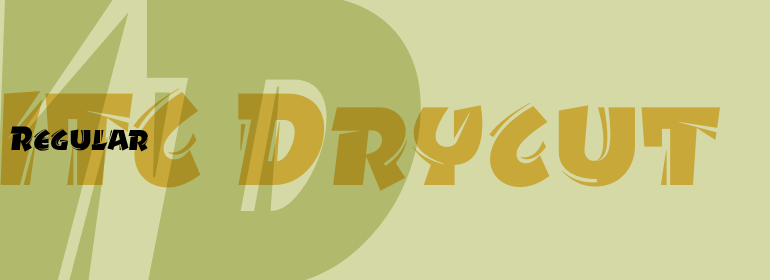
ITC Drycut™
ITC Drycut™,这款字体结构工整、笔画清晰,兼顾美观与易读性,适用于标题、正文、海报、包装、LOGO 等多种场景。字形优雅稳定,风格百搭耐看,适配日常排版与创意设计,让文字呈现更舒适、更具质感。ITC Drycut™一笔一画,皆是细节,以均衡的比例、流畅的线条打造舒适视觉体验,字形端正大气,风格简约现代。无论是商业设计、品牌宣传还是日常排版,都能轻松驾驭,让文字更有格调与力量。ITC Drycut™字体下载。
ITC Drycut是温哥华设计师Serge Pichii的作品,它改变了传统的木刻风格的字体。该字体囊括了木刻所有的真实特征,锋利的边缘、白色的刻痕以及黑色的木片。字体边缘的木片表明了刻刀笨拙地移动后留下的痕迹,这些在古老的木刻上经常可以看到... 民间艺术家通常都不太在意对他们雕刻的改进,只要字母还可读,木片就会留下来。 “小写字母实际上是为了与大小写匹配的小型大写字母。ITC Drycut的字母向右稍微倾斜,使字体具有动态特征。”
ITC Drycut is the work of Vancouver-based designer Serge Pichii and gives a twist to the tradition of heavy, woodcut-like typefaces. The font includes all the realistic features of a true woodcut, sharp edges, white cut marks and black slivers. The slivers around the edges suggest traces left after awkward movements of a knife, which are often visible on old woodcuts...Folk artists often didn't care much about refining their carvings and the slivers would have been left as long as the letters remained readable." The lower case alphabet is actually small caps proportioned to match the capitals. The letters of ITC Drycut have a slight slant to the right which lends the font a dynamic character."